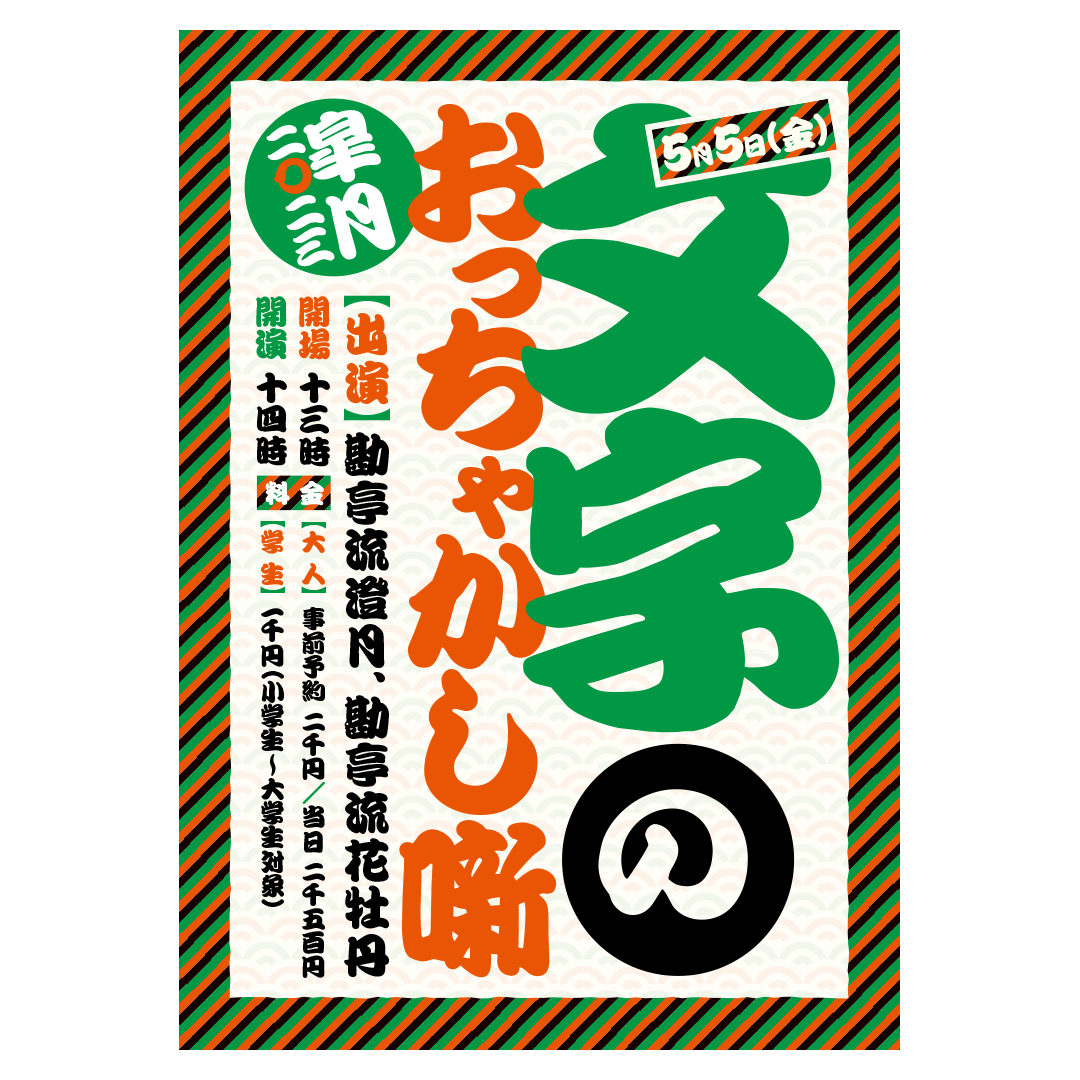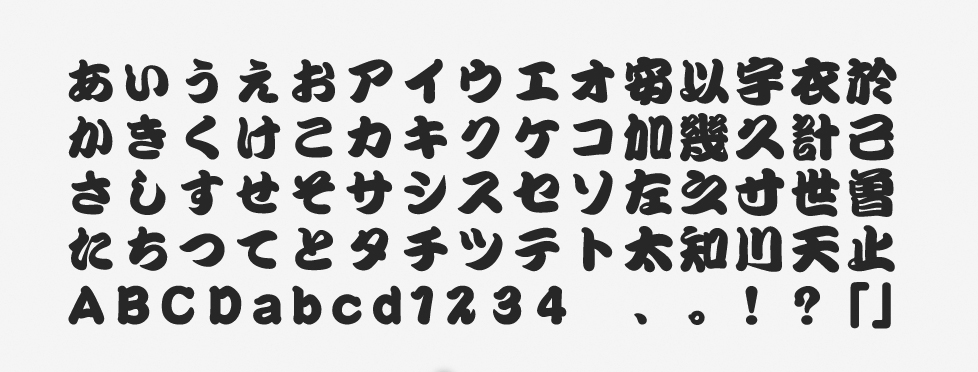
「勘亭流」について
勘亭流は、江戸時代に頻繁に用いられていた江戸文字の一種です。書家の岡崎屋勘六(号名:勘亭)が始めたと言われています。歌舞伎の外題や看板における定番書体で、同じような雰囲気の演劇や、和風のイベントなどに関連した場面での使いやすいも抜群。派手で力強く、目立ちやすいフォントです。
「勘亭流」の特徴
勘亭流の骨格はとにかく太く、うねりのある筆使いであることが魅力です。骨太で威勢の良い江戸歌舞伎の感性がデザインに反映されています。枠いっぱいに隙間なく書かれることも特徴の1つ。これは千客万来を願った “内へと入る” 運筆の表現です。
モリサワの「勘亭流」フォントは、画の間隔をやや広く確保しながら設計されています。文字がつぶれることが少なくて細部の形まで判読しやすく、力強いインパクトがありながらも見やすく仕上げることが可能です。
勘亭流はかなり太い線のフォントなので、タイトルや見出しでの使用がメインです。ただし、「たとえ可読性を多少は犠牲にしても、雰囲気重視で面白くしたい!」という覚悟があれば、小さな文字に使っても独特な効果が得られるかもしれません。文字を絵としてとらえ、グラフィカルなパターンとして利用したり、タイポグラフィとして使ってみても面白いのではないでしょうか。
パンフレット、商品パッケージ、ロゴ、チラシ、看板、WEB、バナー、うちわ